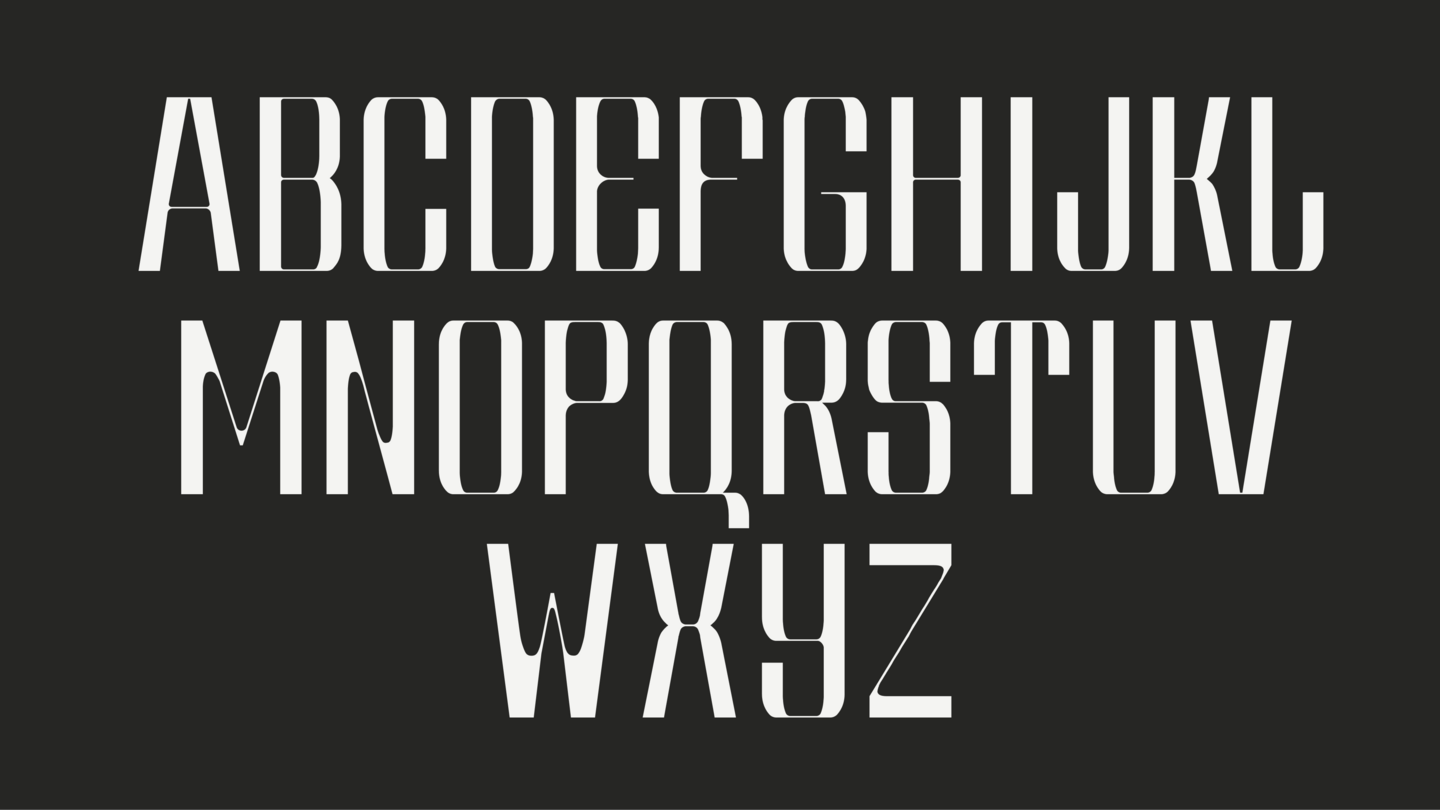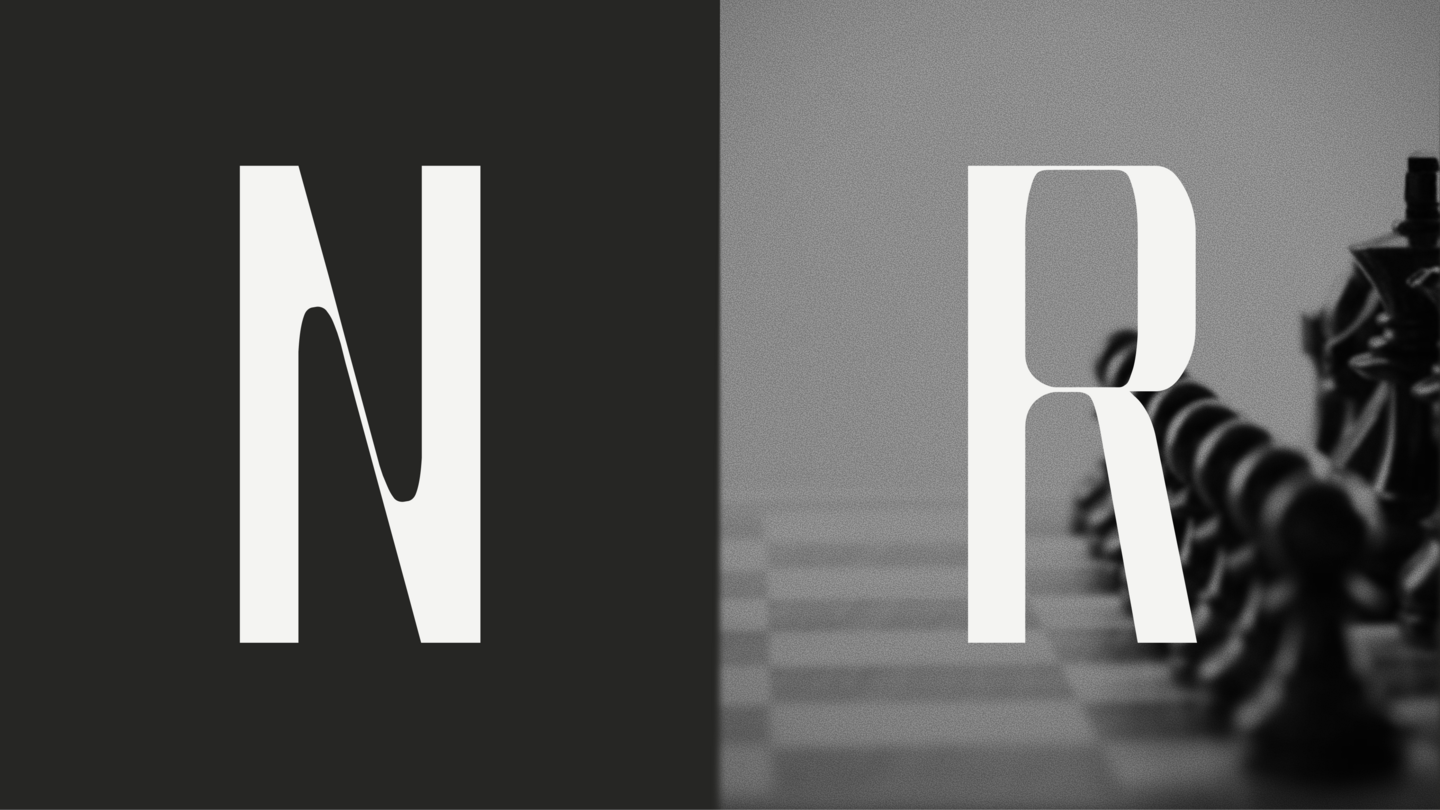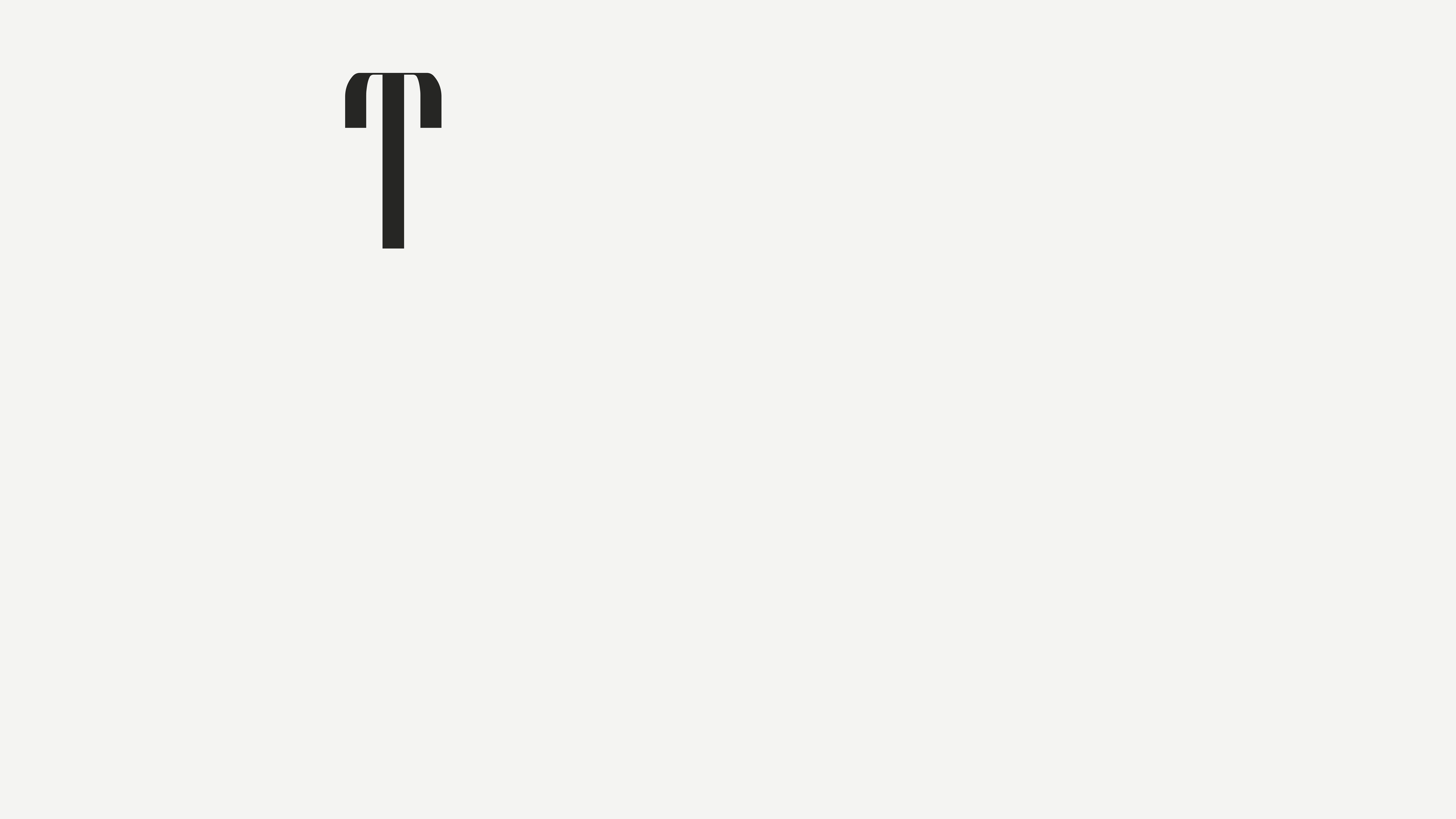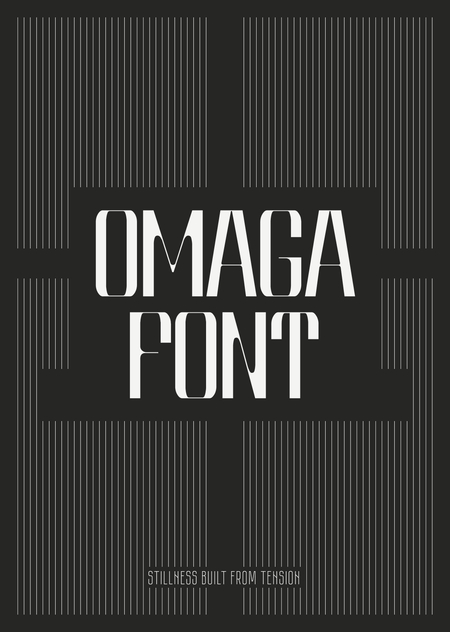
OMAGA FONT — акцидентный шрифт, построенный на внутреннем напряжении формы.
Контраст толстых и тонких штрихов создаёт ощущение сосредоточенности и контроля.